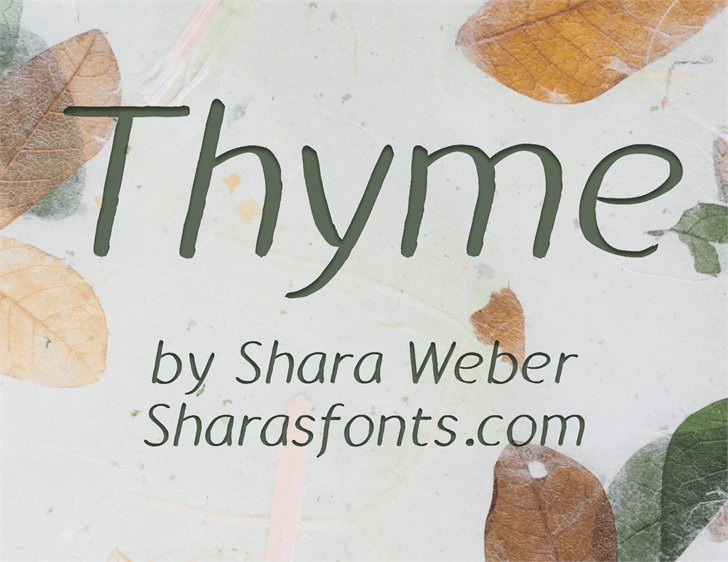
A Thyme Font é uma fonte leve e divertida ideal para criar mensagens envolventes e alegres que certamente vão chamar a atenção dos seus destinatários. Ideal para sites de entretenimento, newsletters ou até mesmo como fonte de design gráfico casual, essa fonte vai fazer sua mensagem soar fresco e desafiador. Inspirada no estilo descontraído da Thyme, uma marca de café popular em todo o Brasil conhecida por suas bebidas leves e alegres, a fonte se destaca na categoria de Playful Fonts com um toque de energia vibrante que promete enriquecer qualquer design. Seu criador, Hamilton, fez desta fonte uma escolha fácil para quem busca uma maneira divertida e acolhedora de apresentar seus materiais digitais. É perfeita para aqueles que buscam uma fonte visual para criar experiências de usuário envolventes, sejam elas no ambiente digital ou físico.